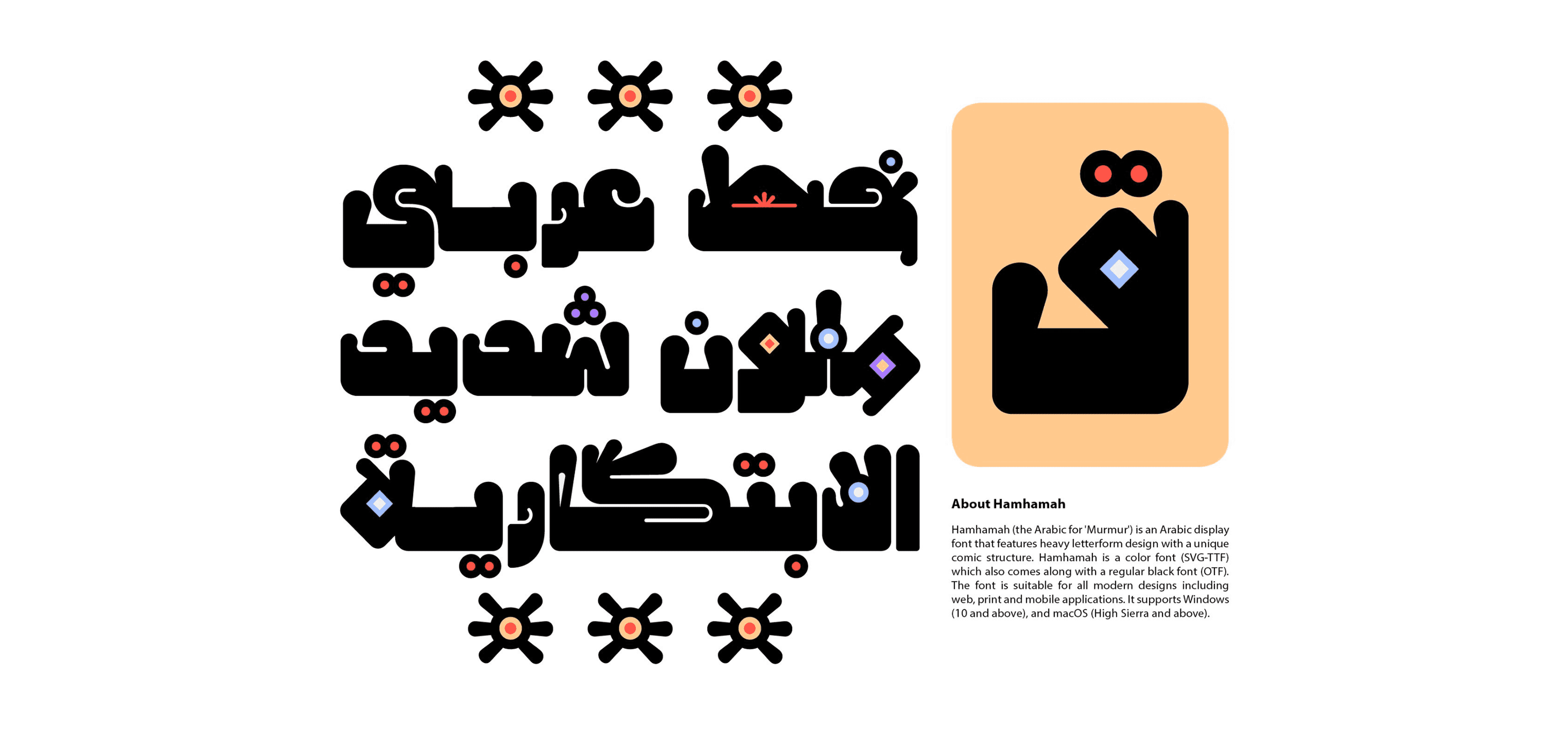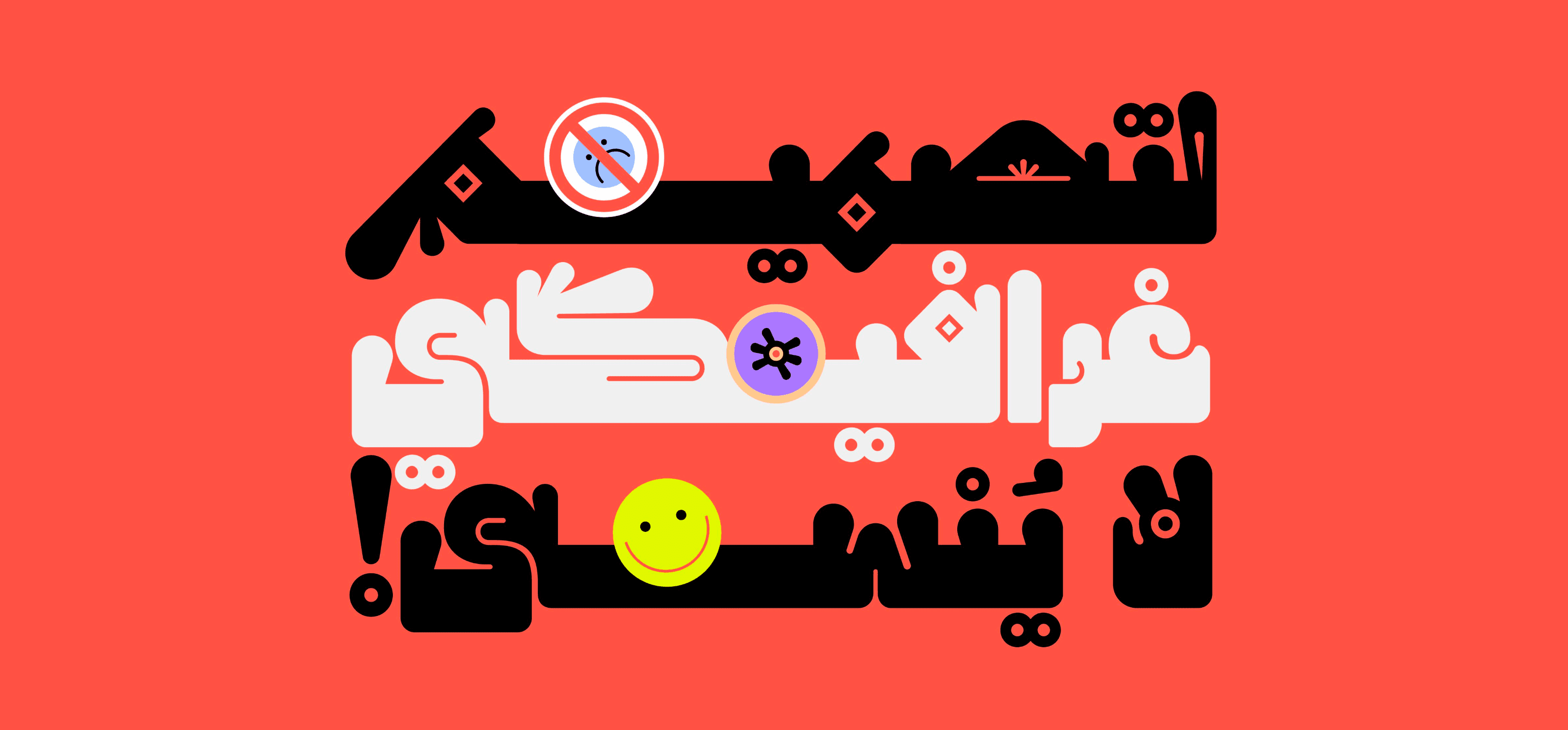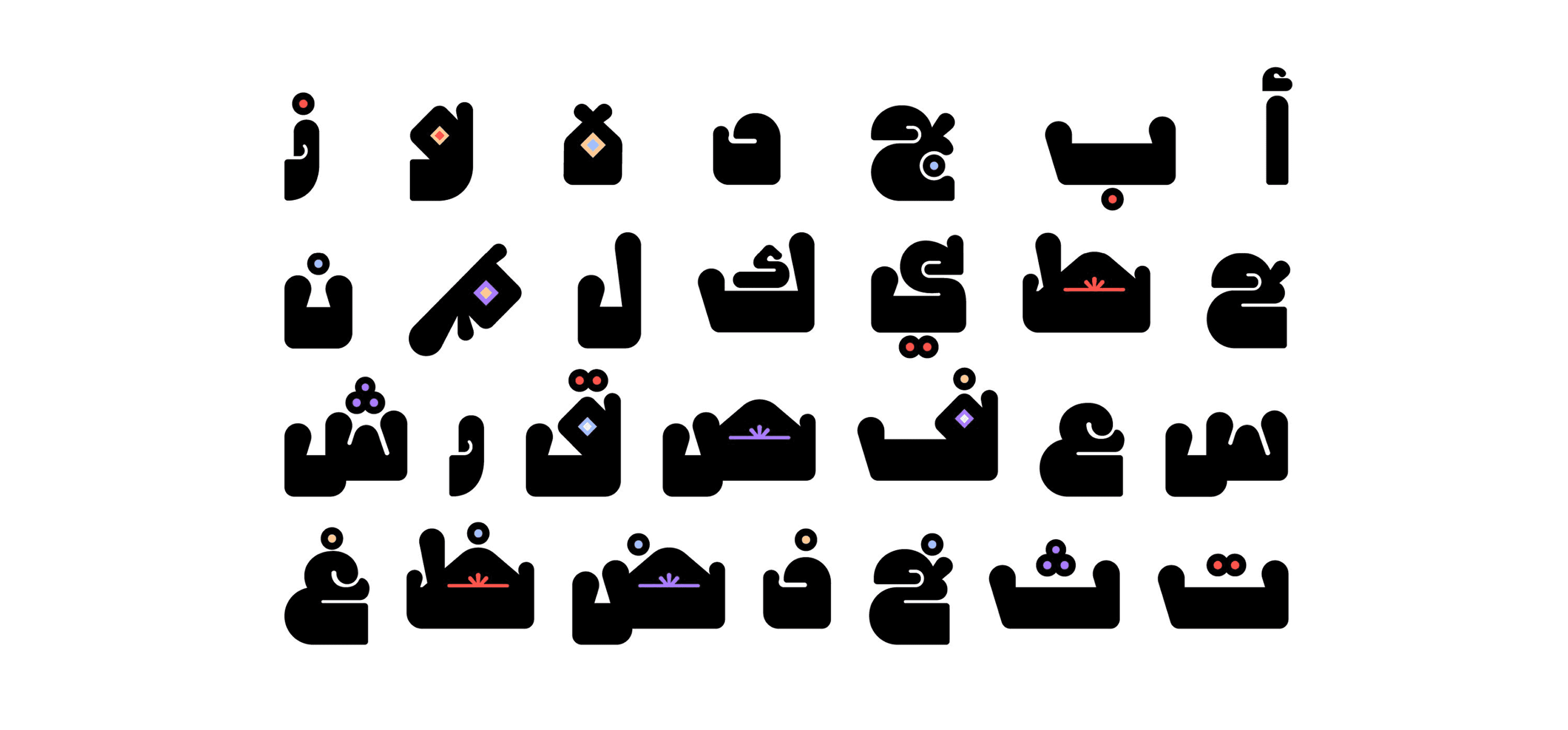
خط همهمة – Hamhamah Arabic Color Font
خط عرض عربي يحمل طابعًا فكاهيًا وجريئًا، يتميز بتصميم ثقيل للحروف وبنية مرحة مستوحاة من الأسلوب الكرتوني.
"همهمة" هو خط لوني (Color Font – SVG-TTF)، ويتوفر أيضًا بإصدار عادي باللون الأسود (OTF)، مما يمنحك مرونة في الاستخدام عبر مختلف المنصات.
مثالي لتصاميم الويب، التطبيقات، المطبوعات، والمواد التفاعلية التي تستهدف جمهورًا عصريًا وشابًا.